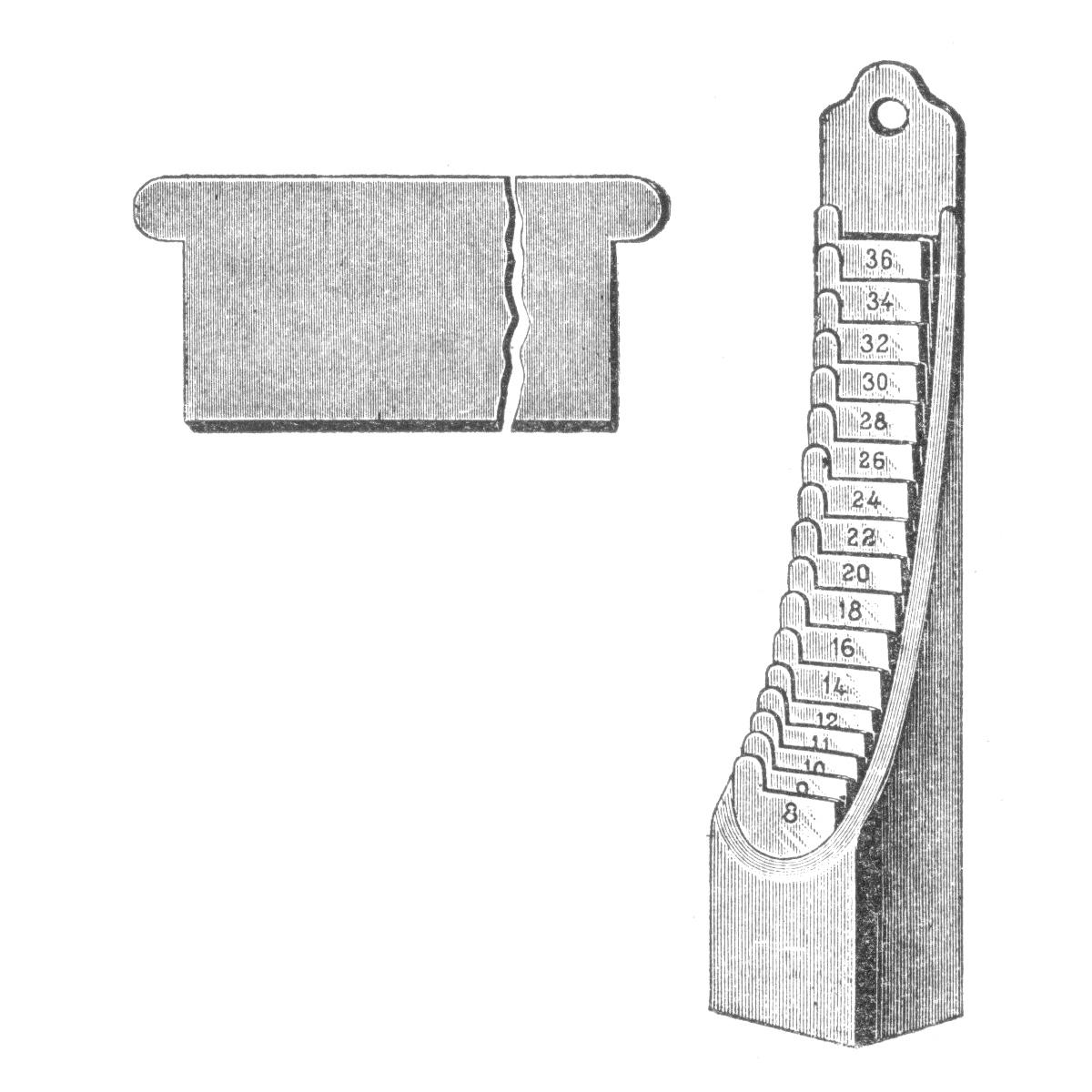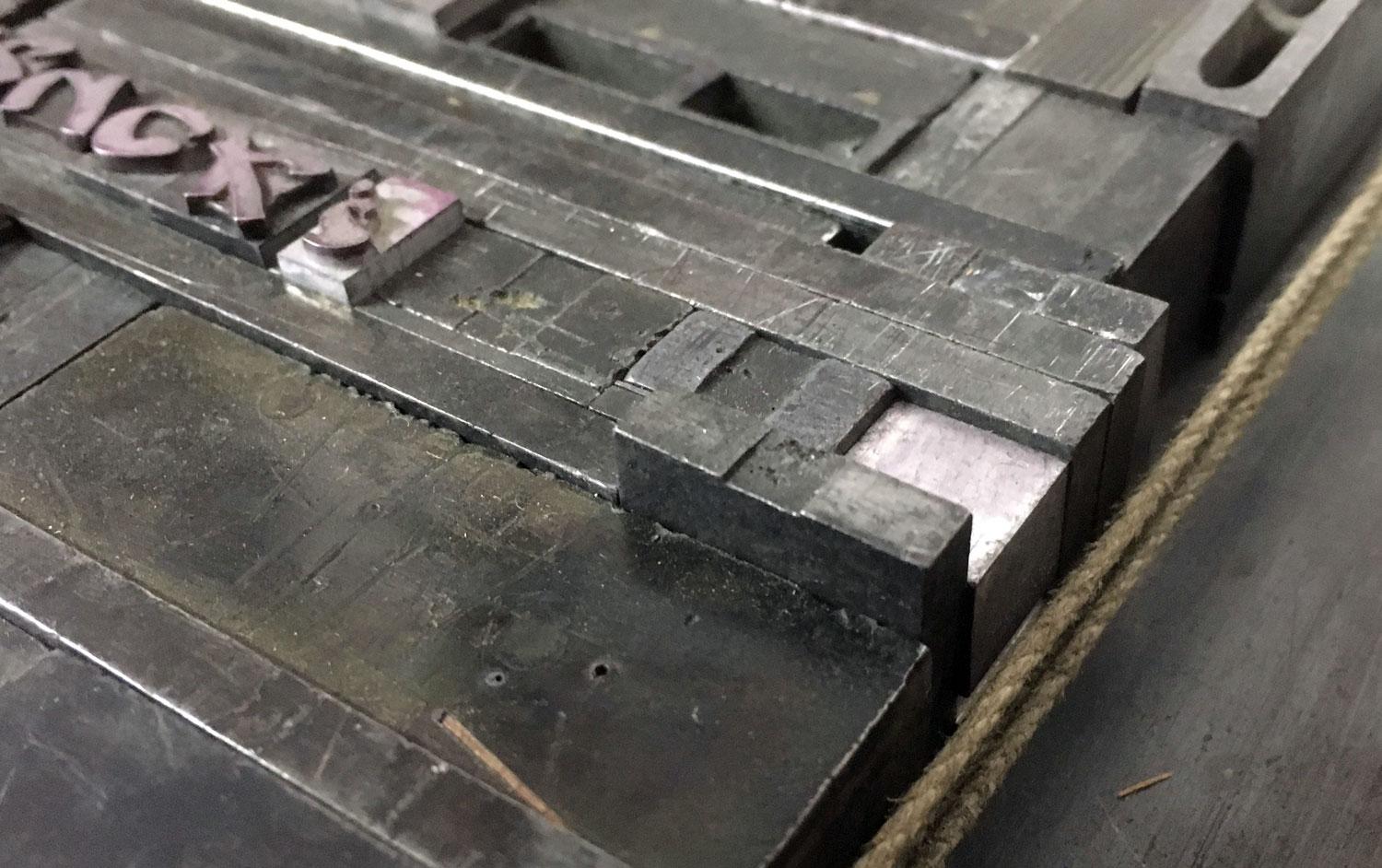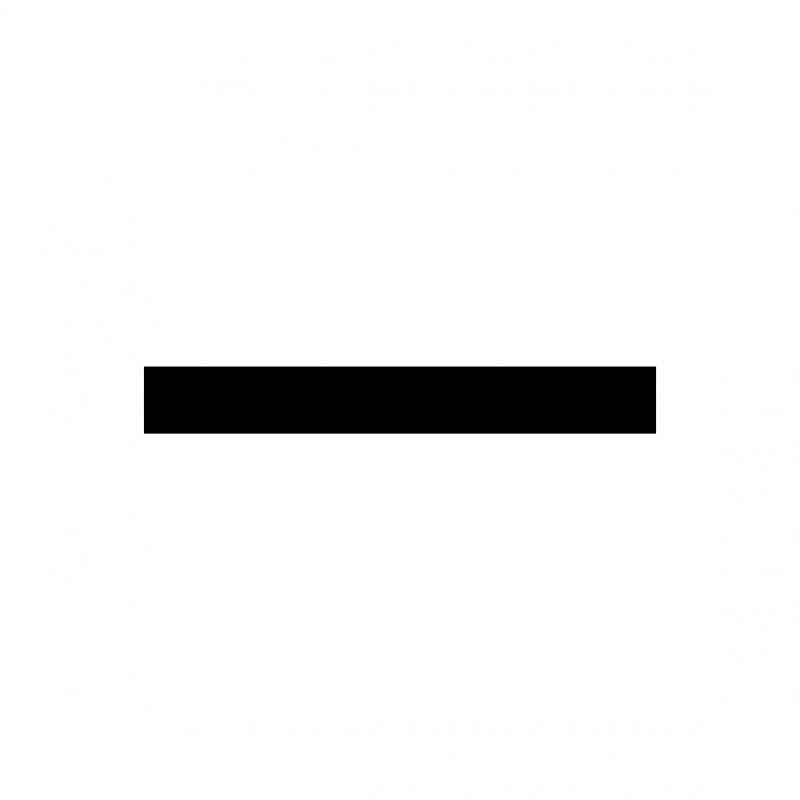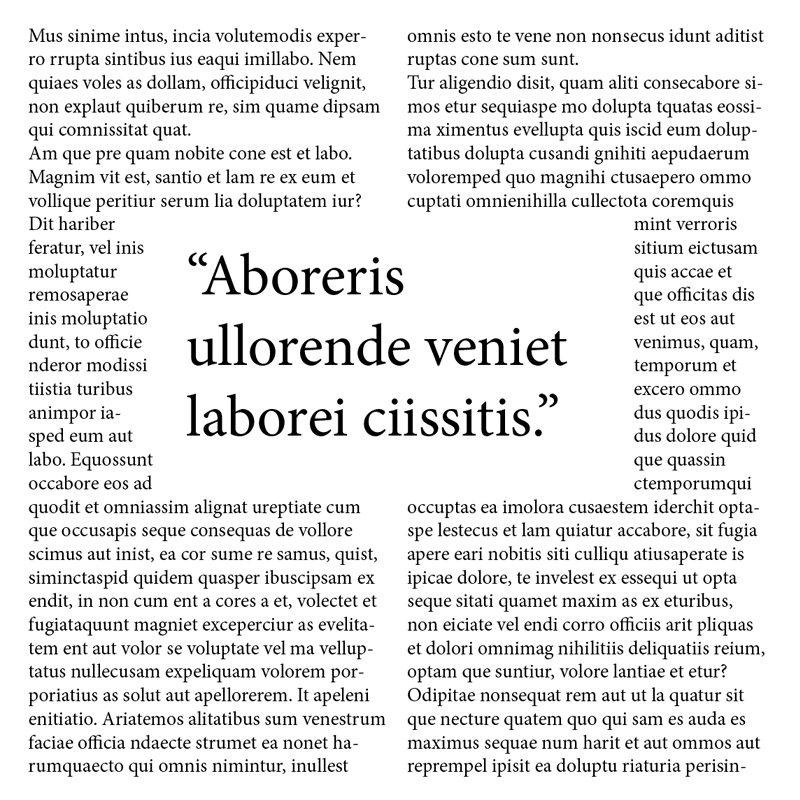
Schriftkästen werden grundsätzlich in Kästen für liegende Schriften und Steckschriftenkästen (ohne Fächer mit aufrecht stehenden Lettern) unterteilt. Steckschriftkästen werden vornehmlich für größere Schriftgrade verwendet.
Setzkasten mit einer liegenden Schrift
Steckschriftkasten
Das Satzschiff ist ein auf meist drei (manchmal auch nur zwei) Seiten mit einem hochstehenden Rand versehenes stabiles rechteckiges Blech. Die vierte Seite (in der Regel eine Schmalseite) bleibt oft ohne diese Begrenzung, damit man den ausgebundenen Satz auf eine Schließplatte schieben kann. Bei vielen Satzschiffen kann man diese vierte Seite auch mit einer herausnehmbaren Leiste »schließen«, wenn diese auch für die Aufbewahrung von Stehsatz verwendet wurden. In die entsprechenden Satzschiffschränke wurden die Satzschiffe mit der offenen Seite zur Rückwand des Schrankes eingeschoben. Damit dabei der Satz auf dem Schiff hinten nicht herunterrutscht, wurde diese Leiste eingehakt.
Das Format der Satzschiffe war höchst unterschiedlich von ganz klein (ungefähr A5) bis ganz groß (ungefähr A1). Viel größer machte keinen Sinn, weil man dann ein mit Blei gefülltes Satzschiff kaum noch tragen kann. Verbreitet waren (vor allem bei der Zeitung) auch sehr lange und schmale Satzschiffe für den sogenannten Spaltenabzug, z. T. auf Andruck- oder Korrekturabzugspressen, die auf Schrifthöhe plus Satzschiffbodendicke eingerichtet waren und somit der Satz nicht vom Schiff gezogen werden mußte.
Eine Zeile Text mit einem g e s p e r r t e n Wort.
Beim Satz auf der Linotype oder der Ludlow kann ein sehr ähnlicher Effekt durch Fehler im Guss oder schadhafte Matrizen entstehen.
Auf der Bodenplatte ließ sich das Trägermaterial horizontal bewegen, um nach der Belichtung eines Buchstabens – der dabei sofort dauerhaft sichtbar gemacht wurde – zum nächsten zu springen. Für korrekte, über die Projektion jedoch zumindest empfohlene Buchstabenabstände musste manuell gesorgt werden. Die Steuerung der Blende und der Schärfe erfolgt automatisch.
Schriftmusterkatalog für das staromat-Gerät
Optimistisch in eine aufblühende Zukunft blickend: Erwin Städeli am staromat, 1971 in Zürich
Die vier Umschlagseiten werden mit U1 bis U4 bezeichnet. Das erste, was man von einer Publikation, sei es nun Buch, Zeitschrift oder sonst etwas, sieht, ist die Seite U1. Schlägt man das Werk auf, schaut man links auf die, bei Büchern in der Regel unbedruckte, Seite U2 (und bei Büchern rechts dann auf den Schmutztitel). Blättert man nun das ganze Werk durch, bis man die letzte Seite umgeschlagen hat, dann ist links die letzte Seite des Werkes und rechts liegt U3, bei Büchern meistens ebenf
Versalien ist der typografische Fachbegriff für Großbuchstaben. Der Begriff leitet sich ursprünglich von den Großbuchstaben ab, die am Anfang einer Verszeile (lat. versus = »Zeile«) standen. Der Singular lautet der Versal, wird aber in der Typografie praktisch nie gebraucht. Die Schreibweise in Versalien zählt neben kursiv, fett etc. zu den Auszeichnungsarten im Schriftsatz. Ein anderes, ebenfalls häufig gebrauchtes Wort für Großbuchstaben ist Majuskeln – im Gegensatz zu den Minuskeln, den
Das Versal-Eszett bezeichnet die Großbuchstabenform des Buchstaben ß (Eszett). Die Erweiterung des deutschen Alphabets um diesen Buchstabens wird seit Ende des 19. Jahrhundert diskutiert. Bis 1941 waren in Deutschland die gebrochenen Schriften für deutsche Texte vorherrschend und in diesen Schriften gibt es nur in sehr seltenen Fällen Großschreibung von Wörtern. Das ß existierte deswegen lange Zeit nur als Kleinbuchstabe, da es für eine Großbuchstabenvariante schlicht keinen Bedarf gab. Seit dem
Mit Condensed wird eine im Vergleich zum Normalschnitt schmaler laufende Schrift bezeichnet. Condensed-Schriften bieten sich auf Grund des geringeren Platzbedarfes zum Beispiel für Tabellen oder Zeitungsüberschriften an. Eine Schrift, die im Gegensatz zur Standardweite noch breiter läuft, wird im Englischen Extended bezeichnet.
Die Versalhöhe beschreibt die Höhe eines Großbuchstabens (z.B. des H) des jeweiligen Schriftschnittes.
LF ist die Abkürzung für Lining Figures – im deutschen Sprachraum in der Regel als Versalziffern bezeichnet.
Anfang des 20. Jahrhunderts schuf der deutsche Grafiker Ludwig Sütterlin im Auftrag des preußischen Kultur- und Schulministeriums zwei Schulausgangsschriften: eine nach lateinischen Schriftstil, und eine zweite als Weiterentwicklung der bis dahin im deutschsprachigen Raum vorherrschenden Kurrentschrift. Letztere bekam in der Folge die umgangssprachliche Bezeichnung Sütterlinschrift. Sütterlin verzichtete in seiner Vorlage auf die typische Schrägstellung der Kurrent und den Schwellzug.